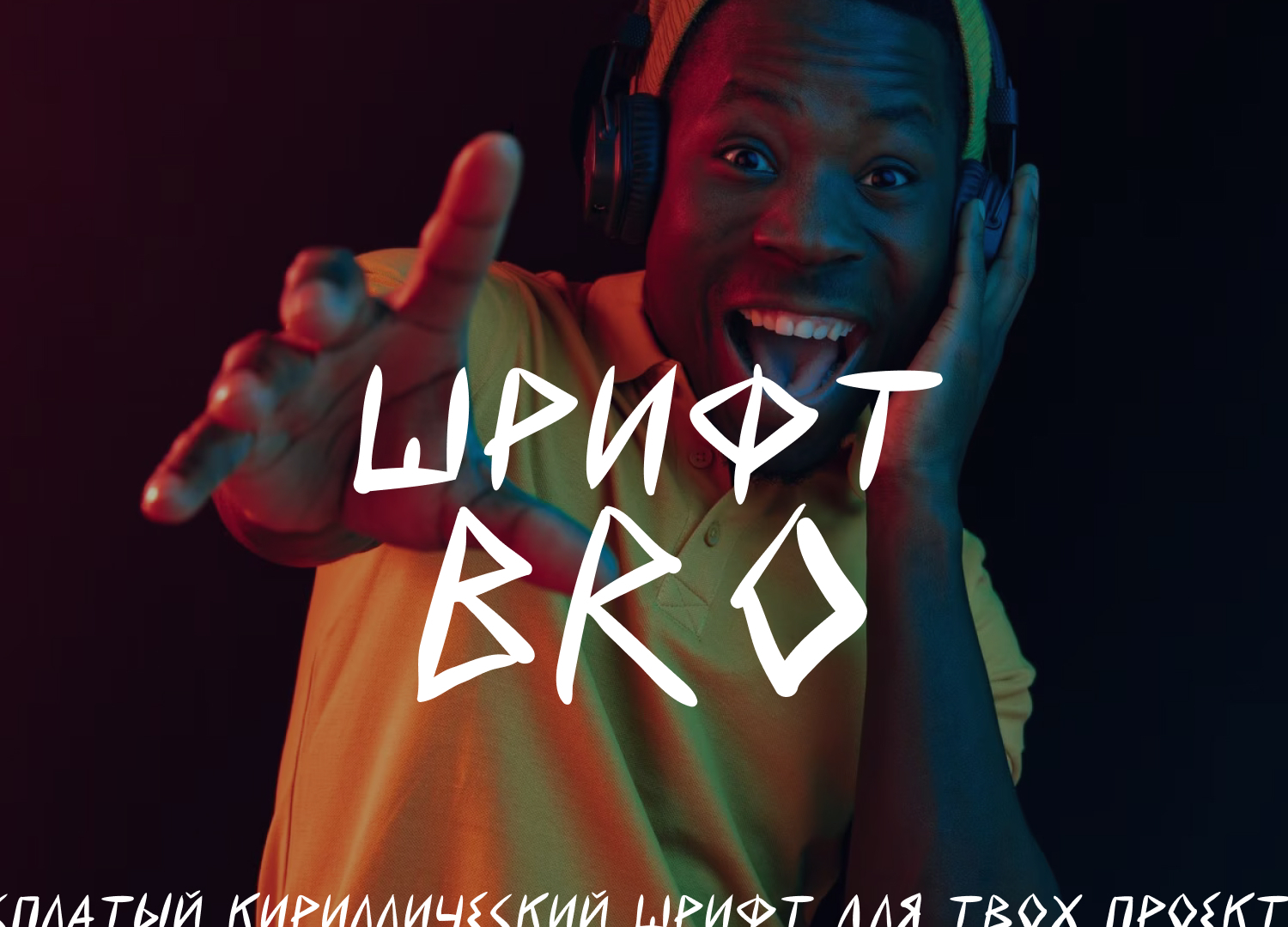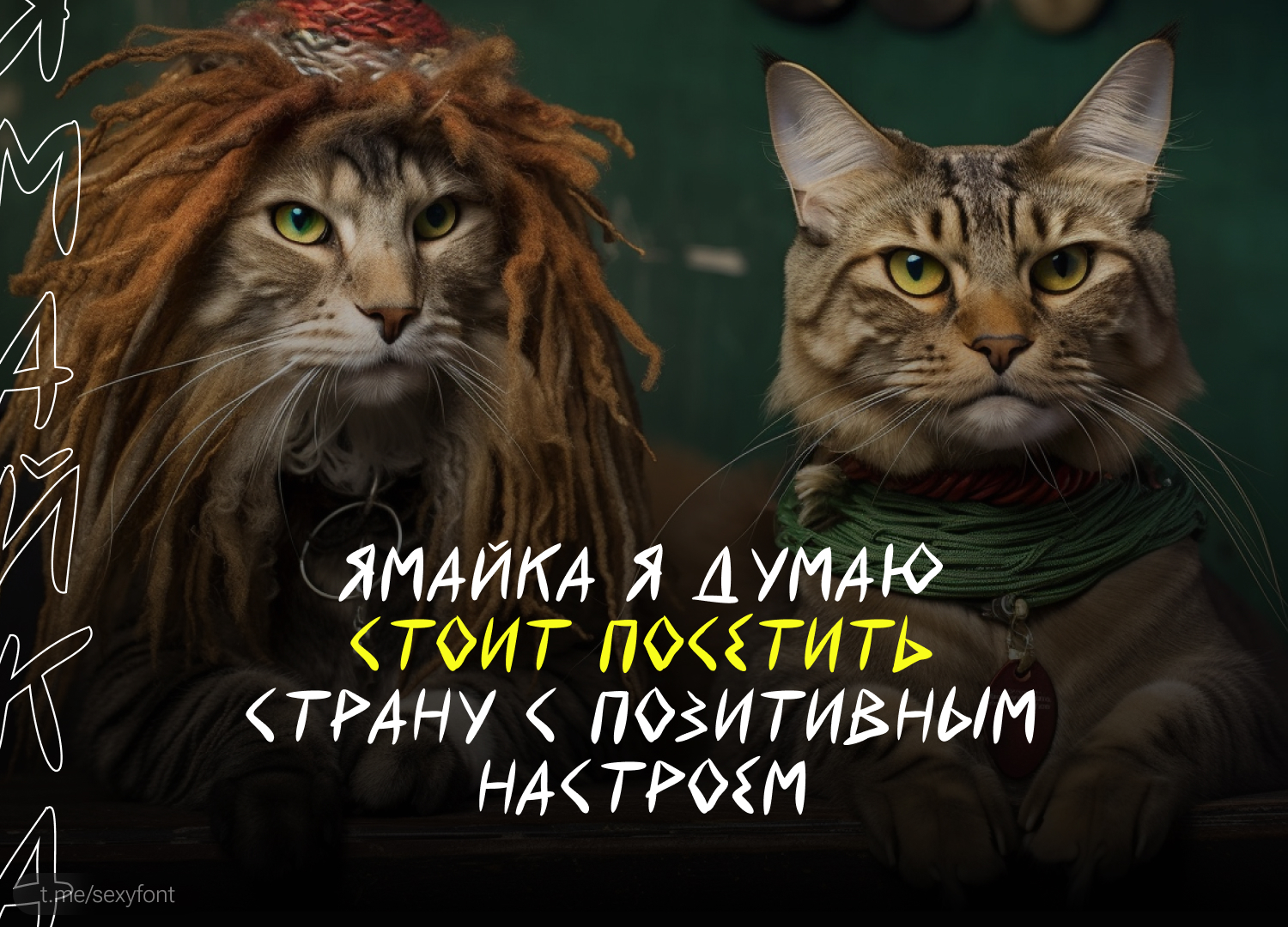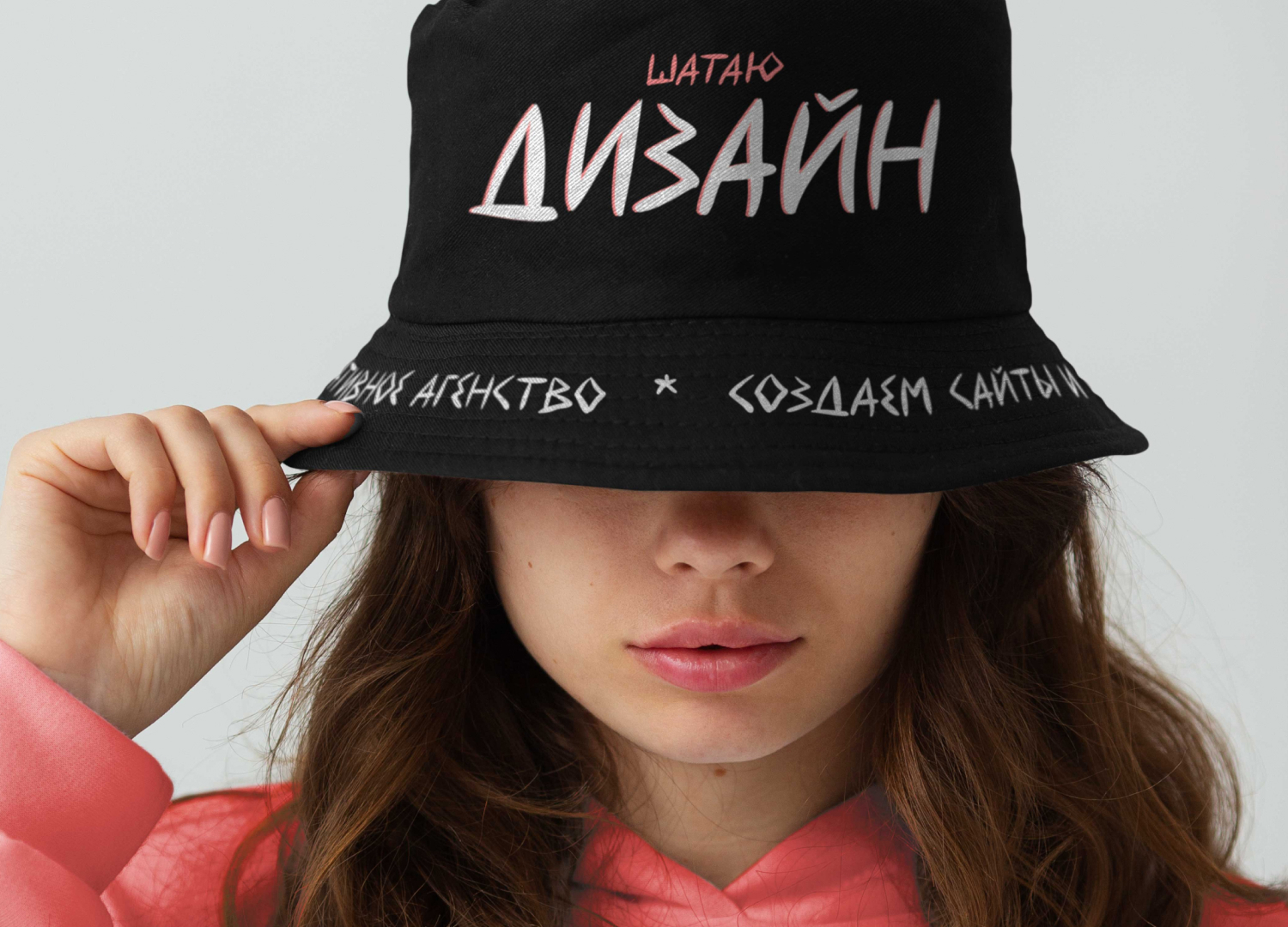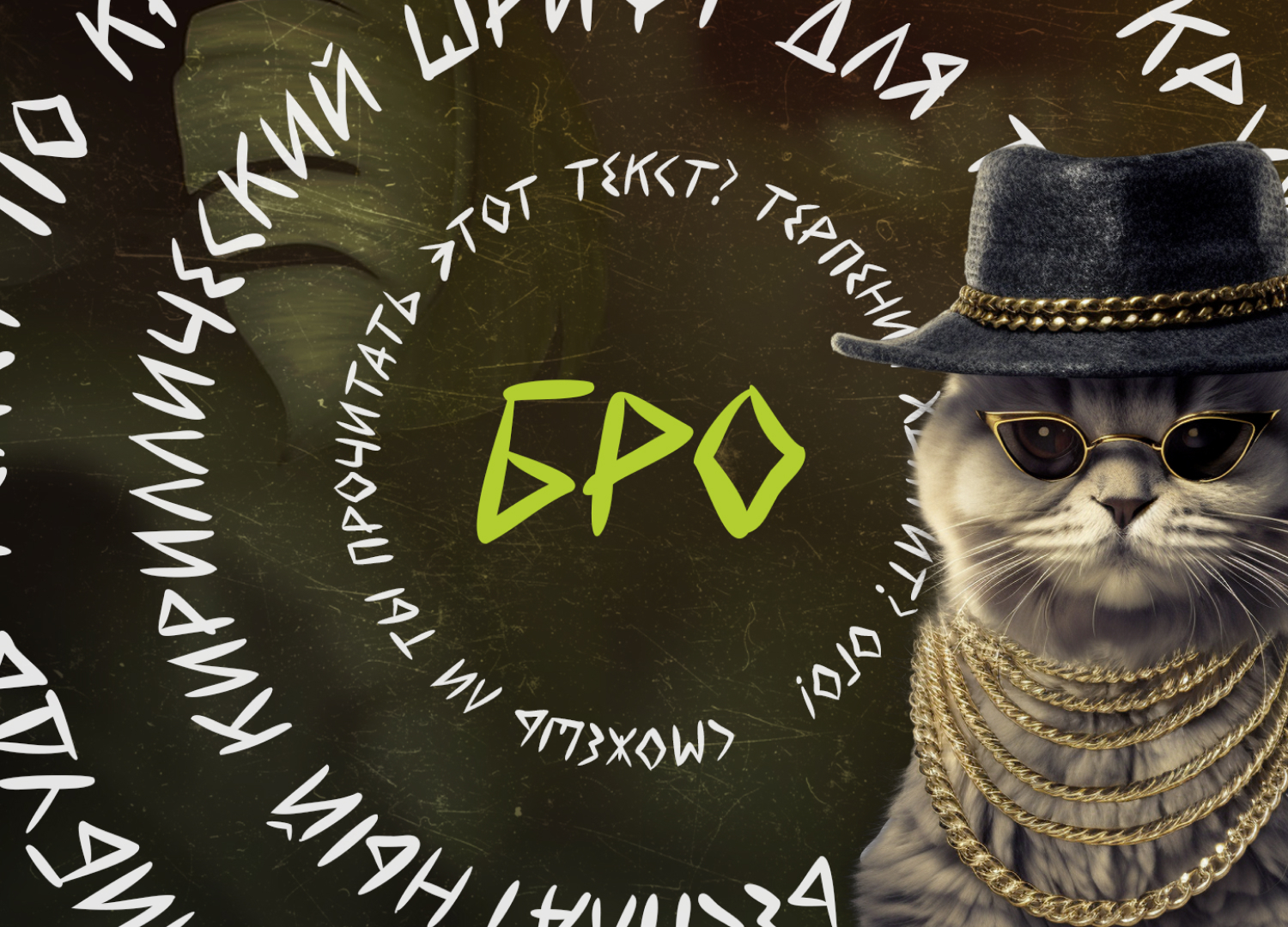
167 Amir74 2 года назад Кириллические шрифты Шрифт Bro Неформальный кириллический шрифтец) Одним словом – бро. Автор: Colorama Studio Бесплатно для личного и коммерции. Скачать в вк | Скачать в телеге со шрифтами [моё] Шрифт Photoshop Кириллица Дизайн Font Длиннопост Ещё 0